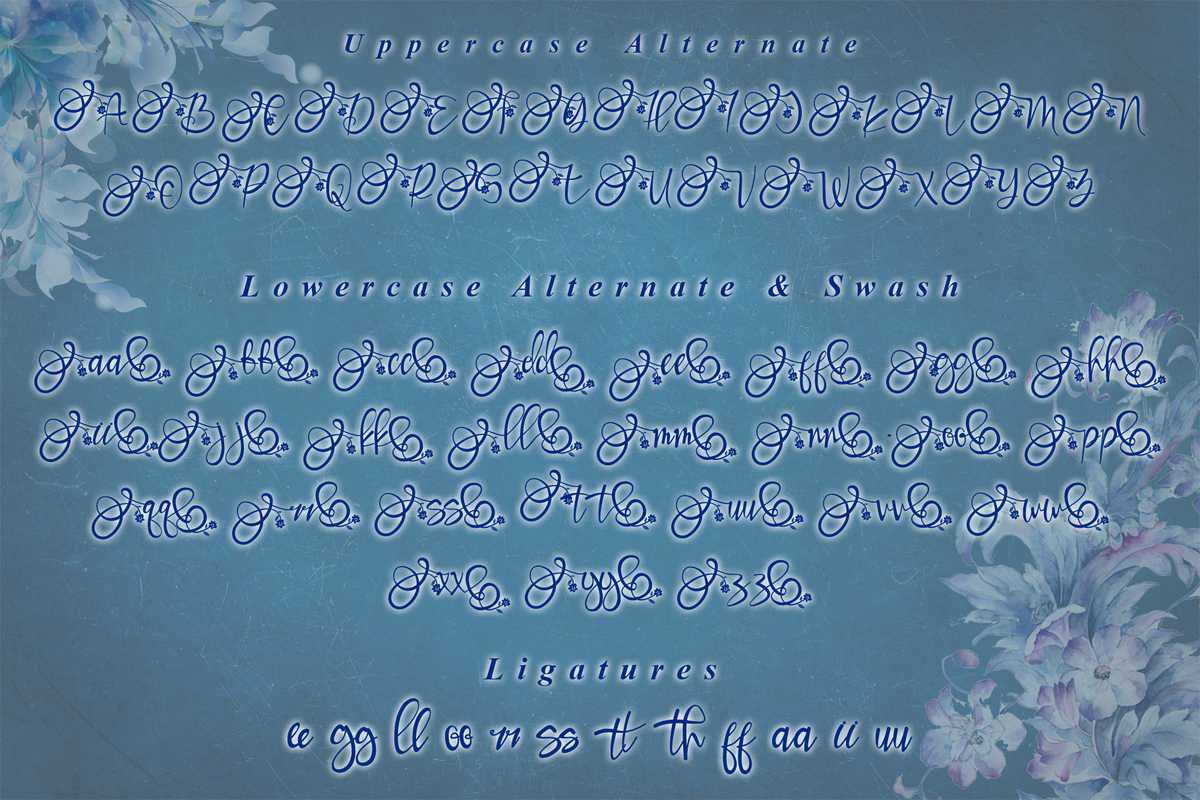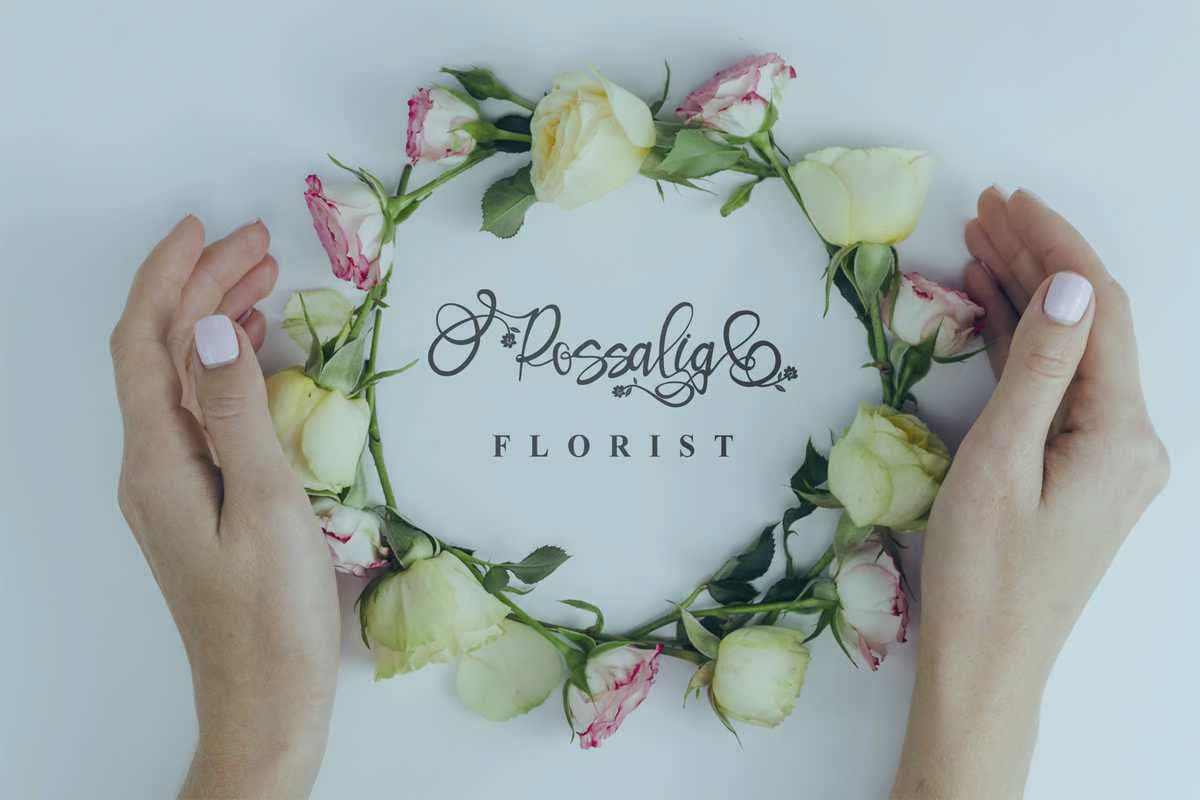
GoodDay将Legance简化为一个真正的Outstanding和WrittenFont。无论您是否正在为项目重新查找FontsforInstagram或CaligraphyScript,此Fonts都是经过编码的,您可以访问此Fonts和Swashese!它还具有丰富的特殊功能,包括交替的PH值和连字。Goodday将Legance简化为一个真正的易读和可写字体。无论您是否正在为项目重新查找字体标记或字体脚本,该字体都是经过编码的,这意味着您可以访问PH值和SWASE!它还具有丰富的特殊功能,包括交替的PH值和韧带。